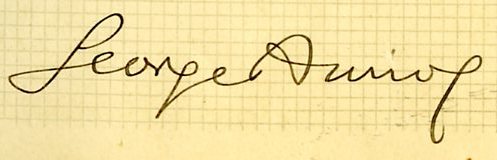
Cher libraire, bonjour...Je suis loin d'être un historien de la lettre d'imprimerie mais ma bibliothèque n'est pas trop pauvre en ouvrages d'Auriol et de Thibaudeau (1) ni en catalogues, donc... 1. _Le Premier Livre des cachets, marques et monogrammes dessinés par George Auriol_ est paru à la Librairie Centrale des Beaux-Arts en 1901 (achevé d'imprimer daté du 3 décembre). A cette époque Auriol avait déjà dessiné le romain et l'ital de ce qui allait devenir l'Auriol de D&P (il l'utilise dans l'ouvrage). Il semble bien qu'à cette date le caractère n'était pas encore fondu (même sous forme d'essai) puis qu'on a affaire dans ce livre à des calligraphies clichées pour être imprimées sur presse typo (je parle, bien-sûr, des textes d'accompagnement, préface de Marx, etc. pas des monogrammes qui sont nécessairement dessinés). 2. Thibaudeau dans son _Manuel Français de Typographie Moderne_ nous apprend (p. 127) : « Si Grasset créa le _romain calamique,_ il était réservé à George Auriol de nous donner le _romain au pinceau,_ ou très exactement "l'écriture typographiée". Cette appréciation que nous portions sur son œuvre dès 1902 [le Manuel date de 1924], n'a fait depuis que se confirmer. » 3. Le premier tome du catalogue DP [sd, vers le milieu des années 1920], lui, nous confie, dans sa préface : « Le lancement du Grasset, puis de la typographie complète d'Auriol, en 1903, retinrent l'attention et chaque effort nouveau des Peignot fut suivi avec curiosité et enthousiasme par les industriels du livre. » On devrait pouvoir en conclure que le romain sortit en 1902, l'ital, la Française légère, la Française allongée et les ornements au plus tard en 1903. Le Robur quant à lui ne sortira qu'en 1912.
Par ailleurs, la signature autographe d'Auriol sur un cahier de dessins de lettres montre bien sa volonté ferme nette et définitive de s'affranchir de l'«s» final de son prénom (voir image jointe). Sans doute une coquetterie anglophilique.
Bonjour à tous Petite question pour les historiens ici présents :Connaitriez-vous la date de sortie de l'Auriol chez Peignot et plus précisement la date de sortie de l'italique ? Pour tout vous dire je serais même preneur du nom des graveurs si vous avez (et de toutes info sur la réalisation de cette ital).indice : c'est 1904 (j'ai sous les yeux un livre de cette date typographié avec) ou un peu avant mais je n'ai pas de références plus tangibles....?!-- Pierre Walusinski